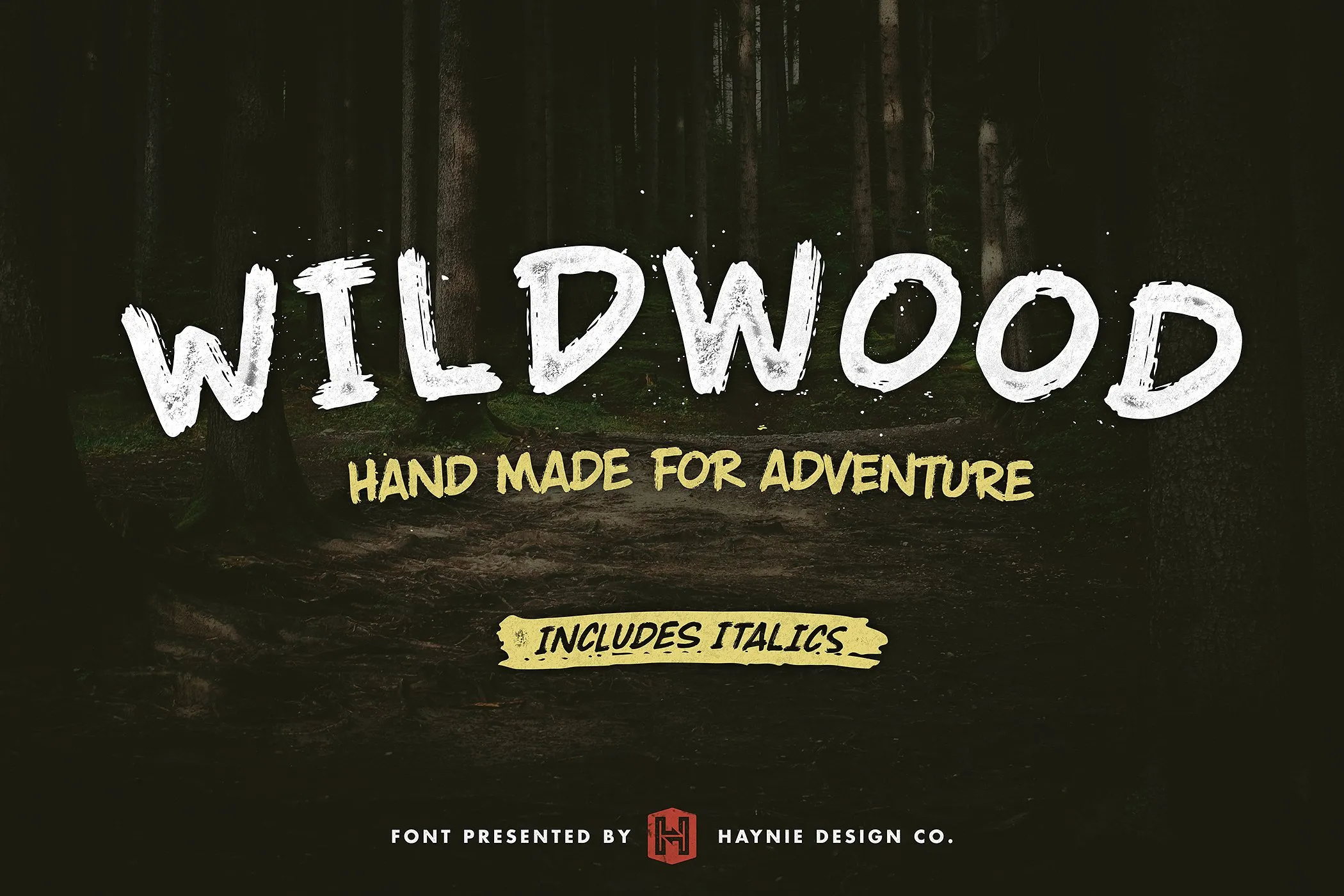
Através do Wildwood Dry Brush Font, criado por Haynie Design Co., você encontrará uma fonte exuberante e expressiva que destaca-se na categoria de Script Fonts. Este é um lote premium disponível no Creativemarket. Ainda não disponível de graça em todas as lojas, podemos informar que a versão gratuita está sendo oferecida hoje para download. O Wildwood Dry Brush é perfeito tanto para trabalhos vintage quanto para promocionais, frases inspiradoras e muito mais. Ele destaca-se com alternativas de letras caixa minúsculas e variante itálico, proporcionando um toque único de arte manual. Através dessas alternativas de letra caixa minúscula e os swashes incluídos como benefício adicional, a fonte Wildwood se torna perfeitamente adaptável para uma ampla gama de projetos. Uma vez instalada em seu sistema de design, o Wildwood Dry Brush será um recurso inestimável para aqueles que desejam dar vida aos seus trabalhos com um toque autêntico e elegante.